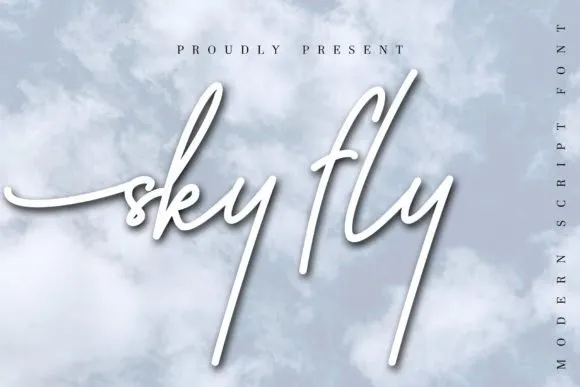
A Sky Fly Font é uma elegante fóntica elaborada por Nox Studio com finuras variáveis e gestos encantadores. Seu design é moderno e sofisticado, perfeito para criar logomarcas impactantes, marcas de marca e citações. Com o PUA (Personal Use Allowed) codificado, você pode acessar facilmente todos os caracteres e swashes, tornando a fonte uma opção ideal para designers em todo o Brasil. Ideal tanto para aqueles que desejam um design minimalista quanto para criar designs com um toque de criatividade, essa fóntica combina perfeitamente entre as categorias de Script Fonts e modernas, sendo uma escolha acima do normal para qualquer projeto gráfico no nosso país.